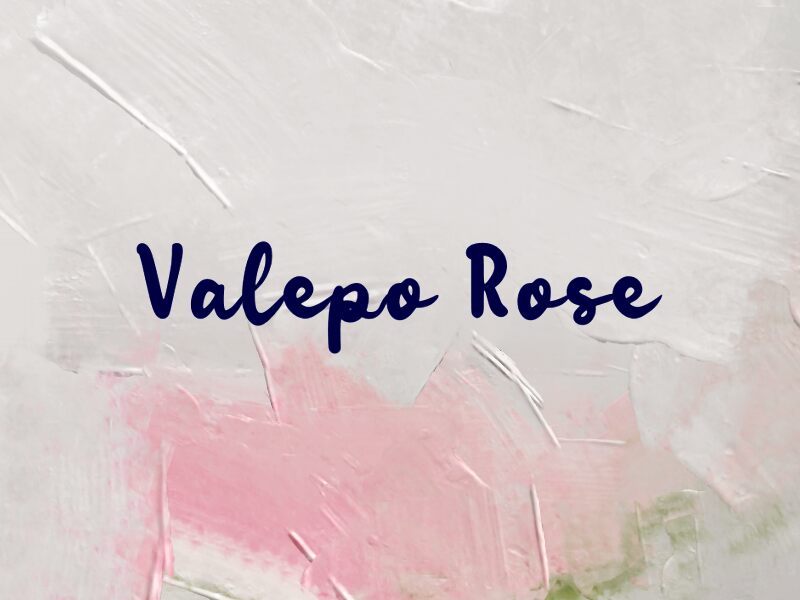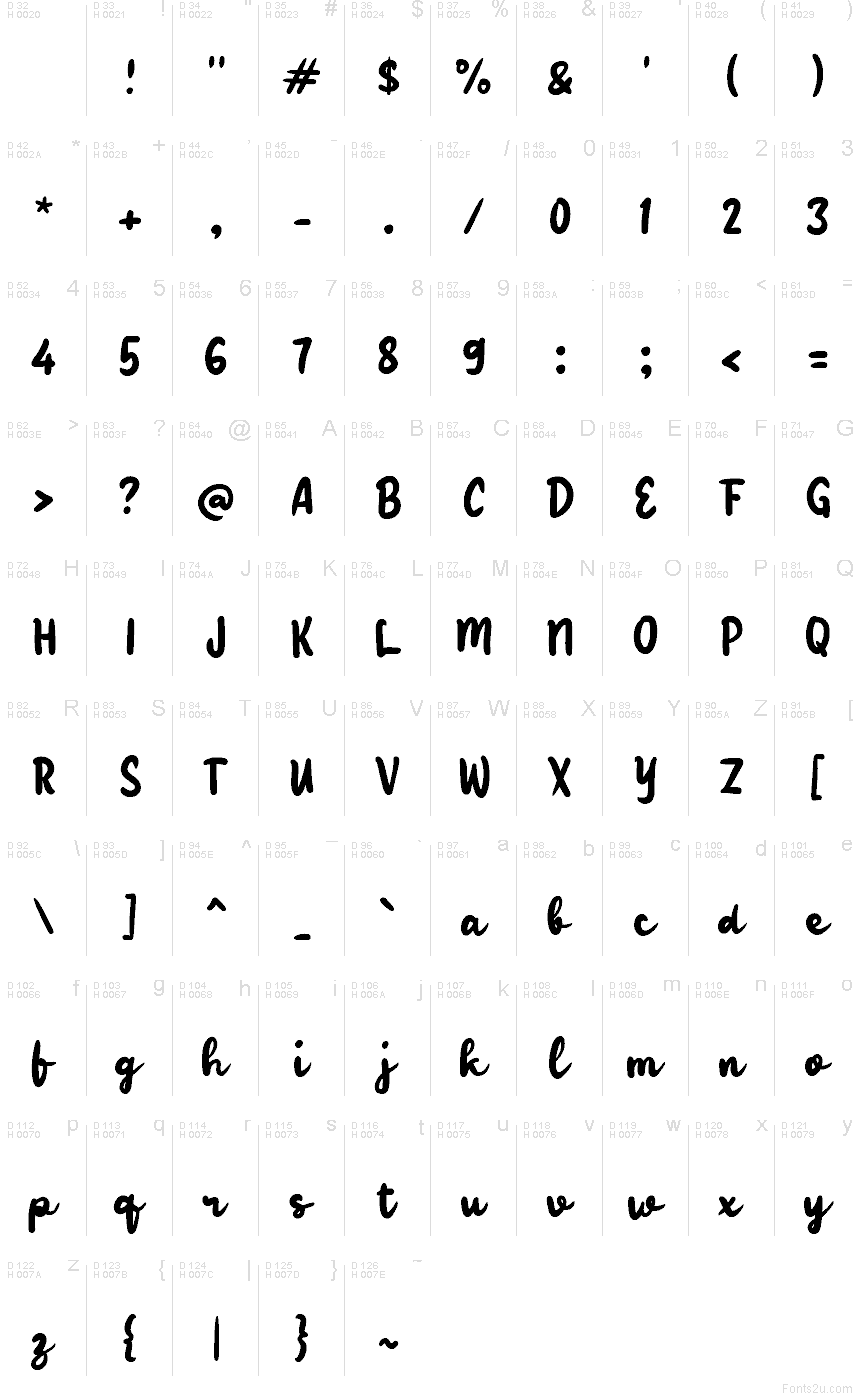
Valepo Rose от Wep — это бесплатный кистевой шрифт с мягким, рукописным характером. Буквы движутся в одном темном, плавном росчерке, сочетая широкие округлые формы с петлеобразными соединениями и слегка игривым ритмом, который ощущается скорее непринужденным, чем выверенным.
Он отлично подходит для оформления соцсетей, брендинга кофеен, упаковки товаров, заголовков плакатов и коротких подписей, где теплое рукописное начертание помогает оживить макет. Будучи бесплатным шрифтом, он особенно полезен для быстрых логотипов, дизайна наклеек и карточек, так как плотная текстура кисти и длинные соединительные штрихи придают даже коротким фразам ощущение легкости и движения.
Valepo Rose
Презентация и наглядный образец шрифта Valepo Rose